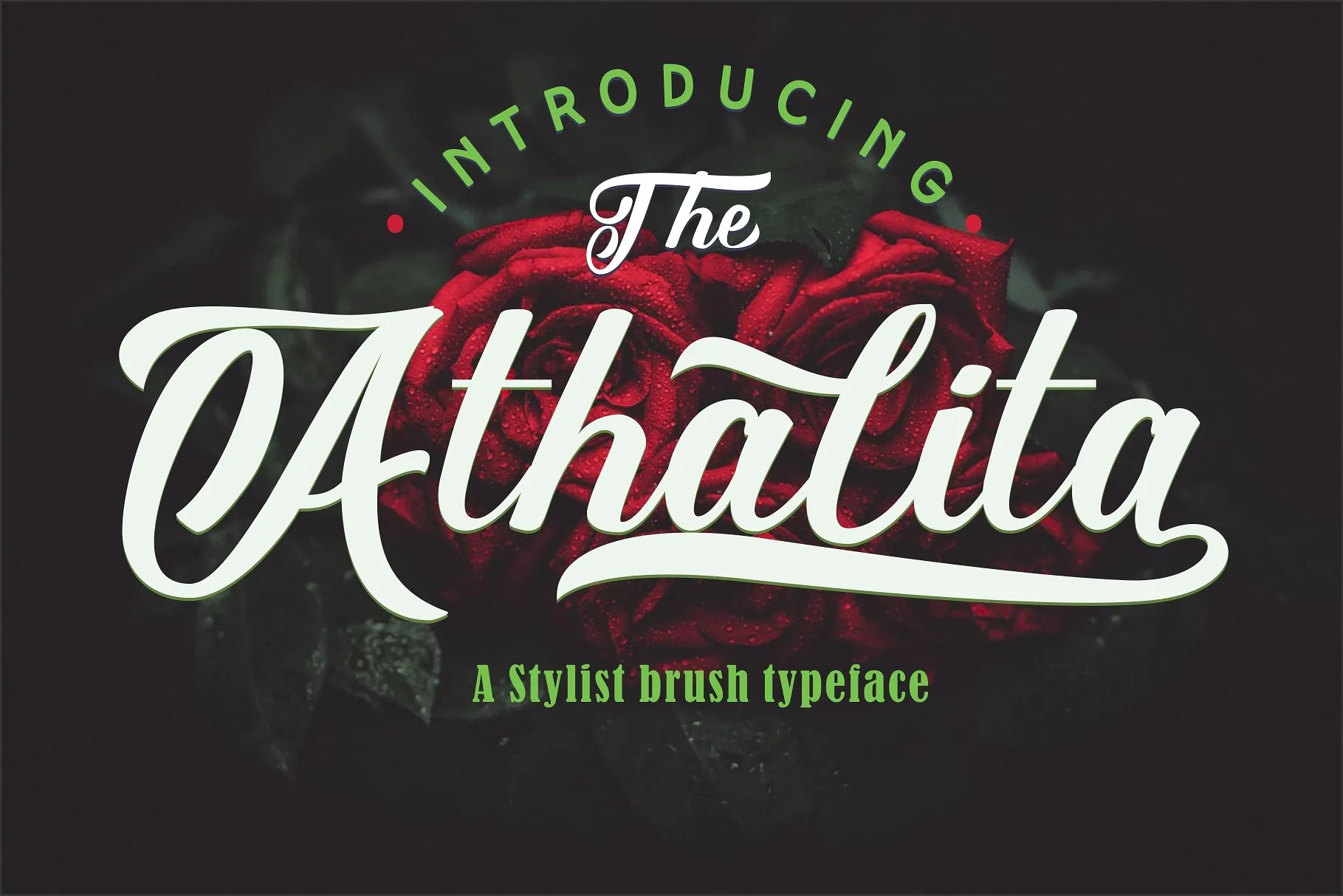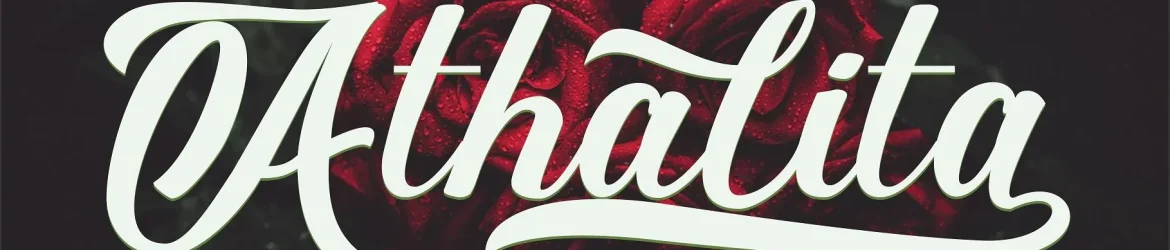
Descubra a essência do design gráfico com Athalita Font, uma tipografia estilizada com o estilo dos traços feitos à mão. Introduzida pelo designer C00zona, Athalita é perfeita para quem busca um blend de elegância e frescura em cada projeto. Seu design com traço de pincel se destaca pela sua versatilidade e facilidade de adaptação a diversas aplicações. Atributos únicos como uma marca d’água impressa em forma circular e a opção de utilizar traços de tipo aberto, oferecem um toque impressionante que tornam Athalita Font não apenas uma seleção para designers estilizados, mas também para aqueles buscando incorporar elementos chamativos em projetos digitais. Como sua descrição original menciona, este é um tipo de fonte inspirada nos desenhos ásperos e modernos, que combina facilmente com o estilo casual e elegante da Athalita Font. Para designers atentos ao detalhe, esta tipografia apresenta um toque especial que ajuda a tornar seus trabalhos mais distintivos e imprimíveis. A fonte é uma excelente escolha para qualquer projeto de design gráfico, seja ele para a criação de identidade corporativa, designs digitais ou até mesmo elementos de marca no design web. Englobe a simplicidade e a elegância da Athalita Font em seu próximo trabalho e conquiste um lugar de destaque entre seus concorrentes.